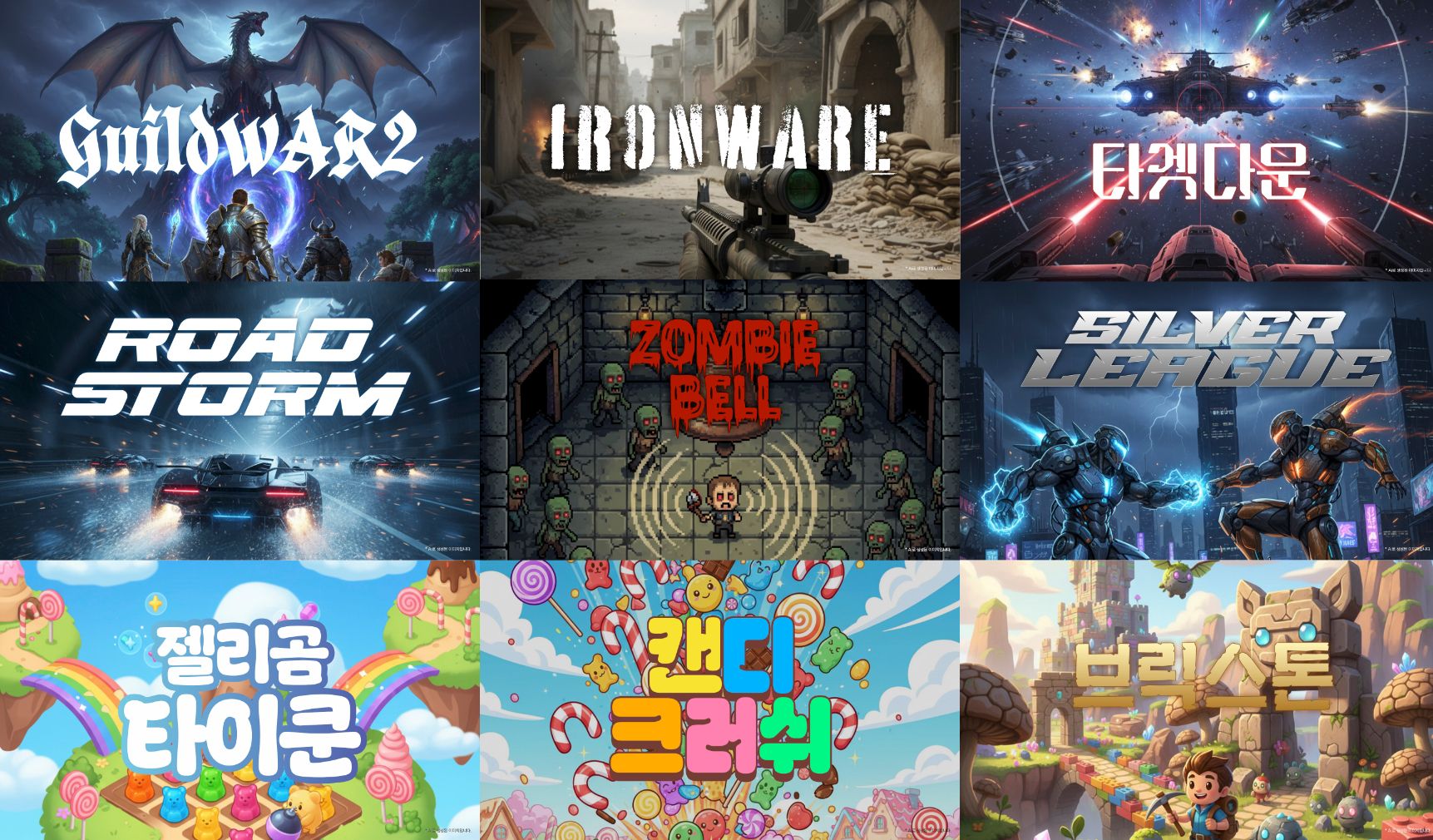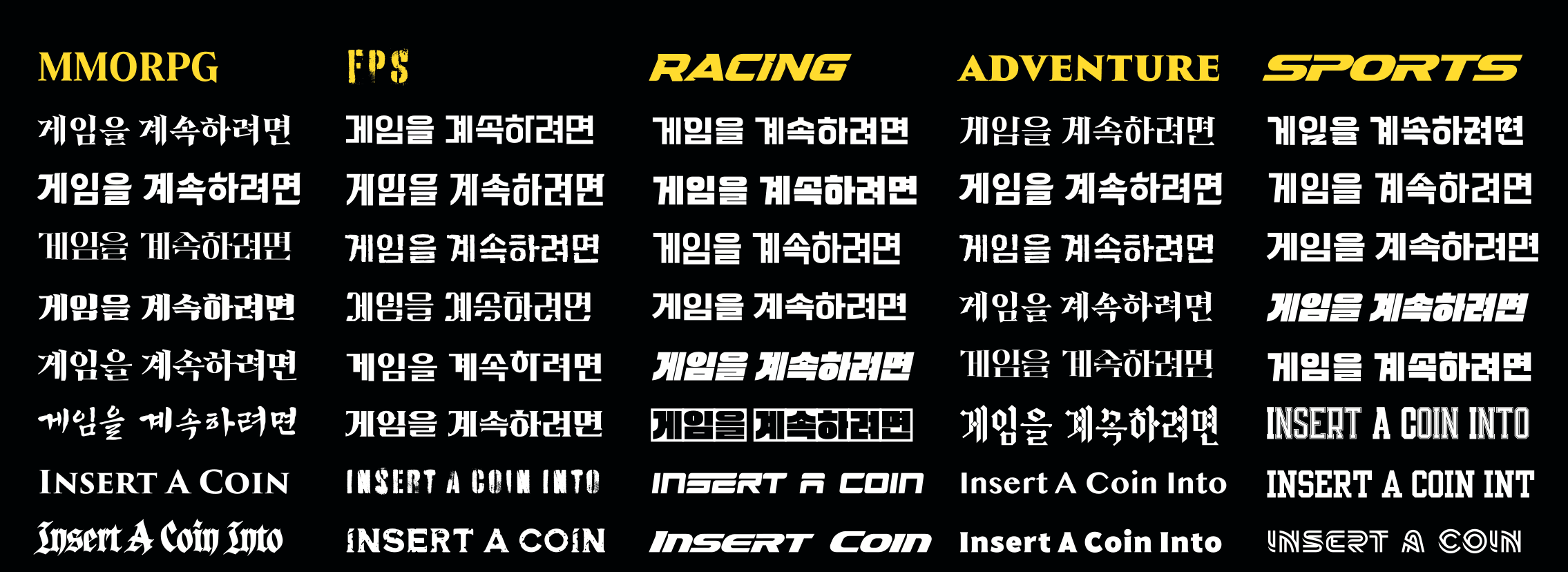
게임과 스트리밍
매끄럽고 완성도 높은 사용자 경험을 위한 전문 솔루션
모노타입은 게임과 스트리밍 플랫폼에서 발생하는 버퍼링, 문자 누락 등 시각적 품질 저하 문제를 효과적으로 해결합니다. 정교한 폰트 렌더링 기술을 통해 콘텐츠의 가독성과 일관성을 높이고, 사용자에게 안정적이고 몰입감 있는 경험을 제공합니다. 또한 글로벌 시장 진출에 필요한 다양한 언어 및 기술적 요구사항에도 완벽하게 대응합니다.
이미지, 게임성, 스토리는 게임을 구성하는 핵심 요소입니다. 그러나 폰트 역시 게임의 완성도와 몰입감을 결정짓는 중요한 요소임에도 종종 그 영향력이 충분히 주목받지 못합니다.
분위기 조성
폰트는 배경음악이나 그래픽처럼 감정과 분위기를 시각적으로 전달하는 중요한 요소입니다. 적절한 폰트 선택은 플레이어를 게임 세계로 깊이 끌어들이고, 몰입감을 한층 높여줍니다.
가독성 향상
가독성이 뛰어난 폰트는 인터페이스의 효율성을 높이고, 플레이어가 게임 내 정보나 스토리를 더 쉽게 이해하도록 돕습니다. 이는 플레이 흐름을 부드럽게 이어주는 핵심 요소입니다.
캐릭터 특성 전달
각기 다른 성격과 배경을 가진 캐릭터는 폰트를 통해 개성을 시각적으로 표현할 수 있습니다. 캐릭터별로 어울리는 폰트를 사용하면 대사 하나하나에도 생동감과 개성이 더해집니다.
글로벌 일관성
다국어 지원은 글로벌 유저와의 연결을 강화하는 필수 요소입니다. 각 언어의 특성과 문화에 맞는 폰트를 사용하면, 전 세계 어디서든 일관되고 완성도 높은 게임 경험을 제공할 수 있습니다.
모노타입 폰트 기술로 폰트 표현 최적화
반복 버퍼링 해결
모노타입의 전문 폰트 기술은 과도한 대역폭 사용으로 인해 제목이나 텍스트가 반복적으로 버퍼링되는 문제를 효과적으로 해결합니다. 특히 비라틴 언어에서도 최적화된 렌더링을 제공해 글자의 로딩 속도와 가독성을 높입니다.
문자 누락 방지
모노타입은 방대한 글로벌 문자 라이브러리를 통해 다양한 언어를 완벽히 지원합니다. 이를 통해 브랜드 이미지를 전 세계 어디서나 일관되게 유지할 수 있습니다. 문자가 누락되면 흔히 '두부'라 불리는 사각형 기호가 표시되어 텍스트를 읽을 수 없게 되는데, 글로벌 확장을 목표로 하는 게임이라면 이런 문제를 방지할 수 있는 폭넓은 폰트 라이브러리가 필수적입니다.
픽셀 렌더링 최적화
모노타입의 픽셀 렌더링 기술은 글자를 선명하고 깔끔하게 표현해 자막과 텍스트가 브랜드의 시각적 완성도에 맞게 표시되도록 합니다. 또한 저해상도 환경에서도 가장자리의 계단 현상을 줄여, 플레이어가 어떤 환경에서도 명확하게 텍스트를 읽을 수 있도록 지원합니다.
전문 폰트 솔루션으로 게임 경험을 한 단계 업그레이드
시간과 비용 절약
성능 최적화
게임 환경에 맞춰 폰트 파일을 최적화하고 맞춤 제작하여 안정적인 성능과 품질을 유지합니다.
크로스 플랫폼 일관성
PC, 콘솔, 모바일 등 다양한 플랫폼에서 동일한 가독성과 시각적 일관성을 제공합니다.
간편한 폰트 관리
손쉬운 현지화 지원
전 세계 디자이너들의 작품이 포함된 방대한 폰트 라이브러리로 250개 이상의 언어를 지원합니다.
창의적 자유 실현
25만 개 이상의 폰트를 갖춘 라이브러리를 통해 게임의 개성과 세계관에 맞는 폰트 스타일을 자유롭게 선택할 수 있습니다.